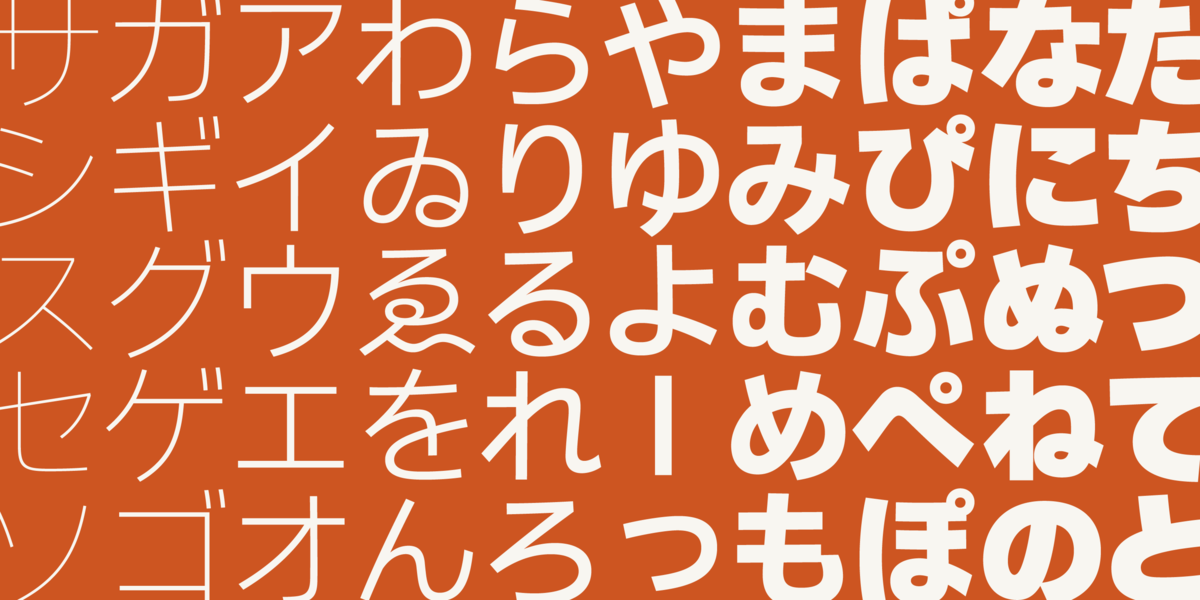
Shorai Sansが2022年度グッドデザイン賞に続いてRed Dot Design Award 2022を受賞
Monotypeは自社の日本語書体「Shorai Sans」が2022年度グッドデザイン賞に続いて、世界三大デザイン賞のひとつである「Red Dot Design Award 2022」のBrands & Communication Design 部門において、Red Dot Award を受賞したことを2022年10月28日に発表した。
Shorai Sans 概要
AvenirR Next [*1]の造形的要素を持つ日本語書体「Shorai Sans」は、たづがねR角ゴシック、たづがね角ゴシック Info に続き、約3年の開発期間を経て完成。
幾何学的でシンプルな美しさと読みやすさが特徴の書体となる。
付属欧文には和文にあわせてサイズや位置を調整した Avenir Next を採用し、和欧混植に最適化した。
たづがね角ゴシック同様、和文と欧文を別々の書体から選ぶ必要がなく、Shorai Sans 単体で美しく読みやすいテキストを組むことができる。
[*1] アドリアン・フルティガー氏と Monotype クリエイティブタイプディレクターの小林章が共同制作した書体ファミリー。オリジナルの Avenir を改刻、ウェイト数を大幅に増やし、OpenType フォントとして2004年に発売。
Shorai Sansの特徴
文字の線をできるだけ整理し、骨格を極限まで単純化。線を均一に保つことで、すっきりと読みやすい明快な形を目指して設計された。シンプルで見やすい文字は、印刷物のほか、スマートフォンやタブレット端末などのデジタルデバイス、建物や標識のサインまで、幅広いニーズに対応している。
文字の太さは超極太から極細までの10種類。
最も太いウェイトの Heavy では、複雑な輪郭線を整理し、Monotype 初の超極太の日本語書体を実現した。
通常の単体ウェイトに加えて、文字の太さや幅などをユーザー側で自由に調整できるバリアブルフォントを採用し、ウェイト間の太さも調整できる。
ウェブサイトや映像などのスクリーン上で動きのある文字表現も可能。
デザイン開発はMonotypeの小林章氏、土井遼太氏、そして書体デザインの第一人者である中村征宏氏によって行われた。基本となる漢字400字ができる頃、Monotype の日本、香港、ドイツオフィスの書体デザイナーとエンジニア、そして中村氏が香港に集まり、1週間ほど一緒に書体制作した。日本語書体の制作では、書体デザインを終えてからエンジニアにバトンタッチするのではなく、両方を同時に進めた方が効率的であると過去の経験から学んだためです。将来の字種拡張も考慮し、最初から多国籍メンバーで開発を進め、世代や文化を超えたコラボレーションとなった。人間らしい自然な筆の動きをイメージしたたづがね角ゴシックに対し、Shorai Sans は「何も足さない『素』のかたち」をテーマに、読みやすくクリーンで理知的な印象の書体に仕上げられた
書体名の「Shorai(ショウライ)」は、松の枝を吹き抜ける風やその音の意味である「松籟」に由来しています。茶道では茶釜の湯がたぎる音を意味し、日本的で優雅な響きのある名前です。誰でも発音しやすく、世界中の方々にお使いいただける日本語書体です。
Shorai Sans(ショウライ・サンズ)